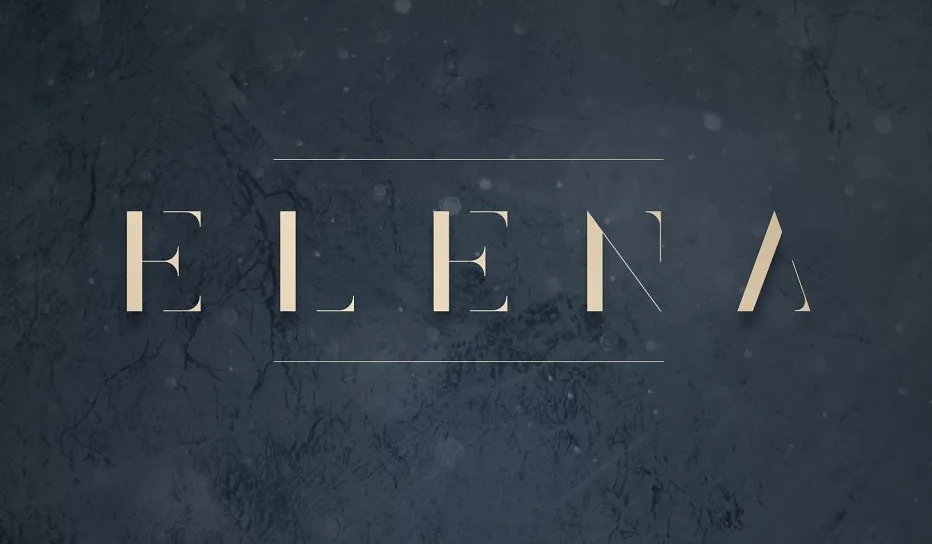
Elena Luxe Serif Font é uma elegante fonte séria criada pela VPcreativeshop. Esta tipografia limpa e sofisticada vem com três variações e suporte a múltiplas línguas, garantindo um amplo espectro de aplicação. Elena é versátil e funciona perfeitamente tanto em grandes formatos quanto em detalhes menores. Seja para projetos de marca, designs de mobiliário ou embalagens de produto; Elena também se torna a escolha ideal para cabeçalhos de revistas e até mesmo como uma transposição estilosa de texto sobre qualquer imagem de fundo. Perfectamente adaptada para um leque amplo de usos gráficos, esta fonte é o complemento perfeito para criar designs impecáveis.